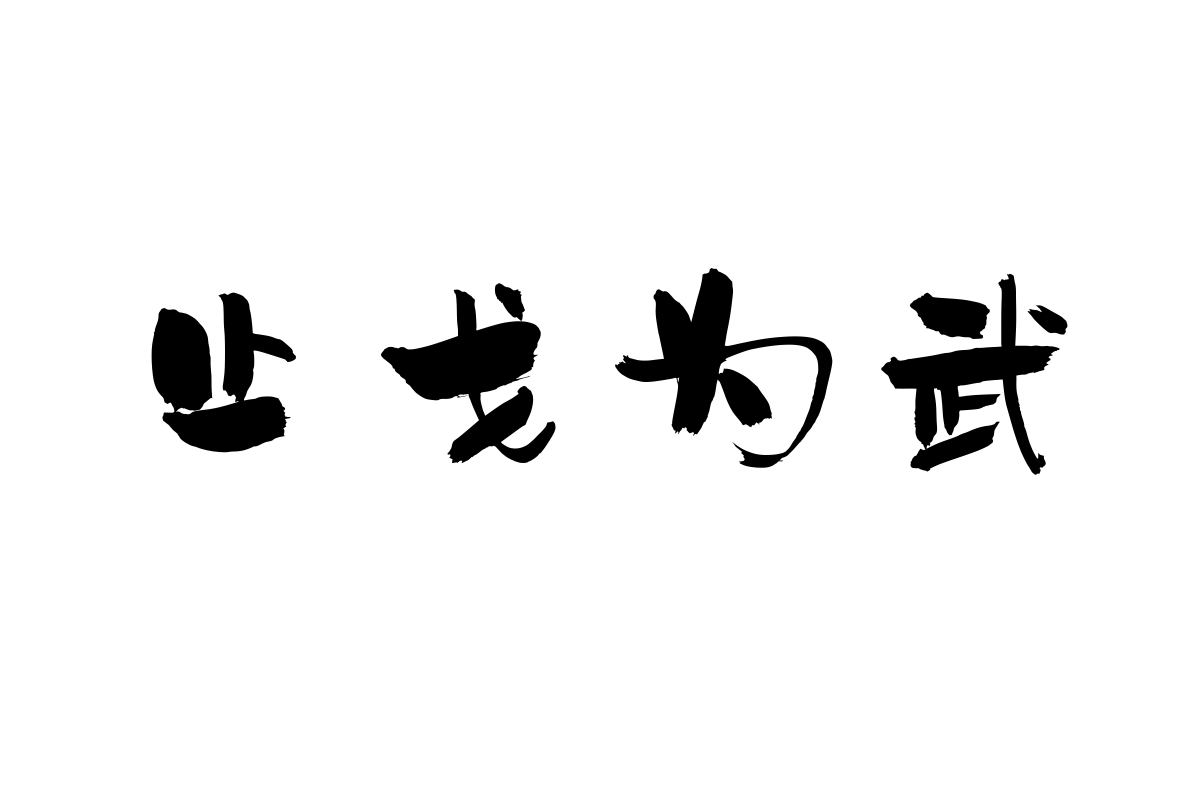
汉仪尚巍流云体是一款具有独特美感和现代感的字体。这款字体的设计灵感来源于自然元素,如云彩、山脉等,给人一种轻盈、飘逸的感觉。它的笔画流畅,结构简洁,既有传统的韵味,又有现代的设计感。
汉仪尚巍流云体的字形特点如下:
1. 笔画流畅:该字体的笔画线条流畅自然,没有过多的装饰和修饰,给人一种简洁、大方的感觉。
2. 结构简洁:虽然字形美观,但结构上却非常简洁,没有过多的复杂线条和形状,使得整个字体看起来更加清晰、易读。
3. 现代感强:该字体的设计灵感来源于自然元素,给人一种轻盈、飘逸的感觉,符合现代审美趋势。
4. 适应性强:无论是在标题、正文还是广告宣传中,汉仪尚巍流云体都能很好地融入其中,展现出其独特的魅力。
总的来说,汉仪尚巍流云体是一款非常适合用于现代设计场景的字体,无论是在网站、海报、杂志还是其他宣传材料中,都能展现出其独特的美感和现代感。